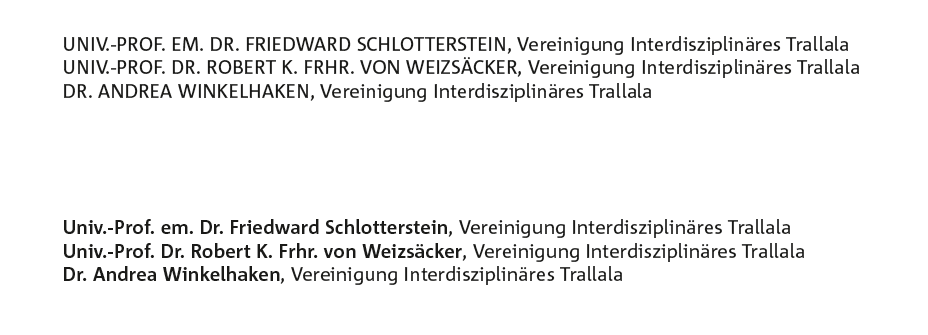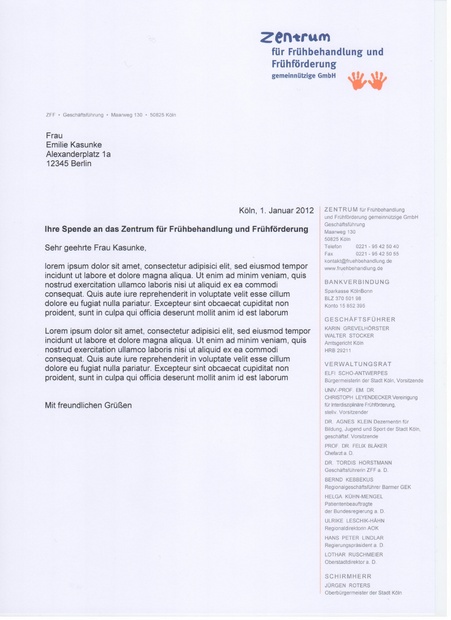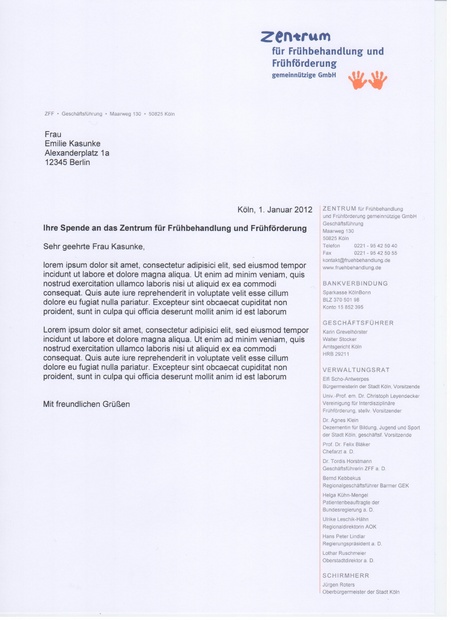
Abkürzung "em." - nur als Minuskel?
ob der häufigen Änderungen in der Besetzung unseres Verwaltungsrates drucken wir, eine gemeinnützige GmbH, die notwendigen Firmenangaben und die zu nennenden Namen direkt auf unser Geschäftspapier.
Namen und Titel der Honorationen sind hierbei jeweils in Majuskeln gesetzt, die Provenienzangabe dann in normaler Klein- und Großschreibung.
Nun haben wir einen emeritierten Professor dazubekommen, dessen Namen ich, dem oben beschriebenen Schema folgend, so gesetzt habe:
UNIV.-PROF. EM. DR. FRIEDWARD SCHLOTTERSTEIN, Vereinigung Interdisziplinäres Trallala
Nun beschwert der Mann sich wie folgt:
"Es ist [...] höchst ungewöhnlich bei meiner Angabe das "em." in Großbuchstaben zu schreiben. Sie sollten das ändern."
Und, soll ich das ändern? Ich habe nach längerer Recherche keinen Hinweis darauf gefunden, dass ich ausgerechnet die Abkürzung "em." nicht als Majuskel setzen darf, so dass ich die Frage gerne in dieses Forum geben möchte: Muss das kleine minuskelige "em." künftig alleine zwischen all den großen Buchstaben stehen?
UNIV.-PROF. em. DR. FRIEDWARD SCHLOTTERSTEIN, Vereinigung Interdisziplinäres Trallala
Sieht irgendwie komisch aus.
Aber wenn er recht hat, kriegt er das natürlich so ...
Es ist höchst ungewöhnlich den Titel und den Namen in Großbuchstaben zu schreiben. Ich würde das gemischt schreiben und – wenn überhaupt nötig – durch eine Fettung auszeichnen. Alles versal und nur das "em." dazwischen klein geht gar nicht.
Entweder den ganzen Titel groß oder gar nicht.
In wissenschaftlichen Werken wird übrigens oft nur der Nachname aus Kapitälchen gesetzt, Vorname und Titel aber gemischt (normal). Eine Möglichkeit wäre auch, Namen und Titel normal zu setzen und die Provenienzangabe kursiv.
Zeige doch mal ein Gestaltungsbeispiel, wie das Ganze da aussieht.
Alle Arten der Schreibung sind möglich, solange sie konsequent umgesetzt werden.
DR. MED.
PROF. EM. DR. PHIL.
Prof. em. Dr. iur.
prof. dr. h.c. dr. dent.
Das em. klein in eine Versalzeile zu setzen, wäre falsch. Der Professor irrt.
Fette Schriften für Namen sind nach alten Akzidenzregeln unzulässig, denn, so hieß es einst: "Man schreit den eigenen Namen nicht." Diese Regel gilt in meiner Werkstatt bis heute, und bislang sah jeder Kunde sie sofort ein.
Alle Arten der Schreibung sind möglich, solange sie konsequent umgesetzt werden. … Fette Schriften für Namen sind nach alten Akzidenzregeln unzulässig …
Das widerspricht sich aber. Zumal ein versal gesetzter Name wesentlich lauter daherkommt als ein gefetteter. Wir sprechen ja immer noch vom Briefbogen, da würde ich (wie oben schon gesagt) alles gemischt schreiben.
Eine fette Futura in Korpus ist sehr viel auffälliger als eine magere Garamond in Petit-Versalien, daran kann kein Zweifel bestehen. Es kommt auch auf die Größe an. Fette Schriften stechen immer hervor, deshalb werden sie auch in der Belletristik nicht zur Auszeichnung verwendet, sondern Versalien, Kapitälchen und Kursive. Fette Schriften sind überhaupt nur in der Reklame nötig oder in Boulevardzeitungen, sonst immer entbehrlich.
Wenn der Briefbogen schon eine Konstante hat, also Namen mit Titel in Majuskeln, dann kann man dabei bleiben. Es geht ja um eine pragmatische Lösung in einem vorhandenen Entwurf, nicht um eine neue Gestaltung. Namen in Versalien sind für Akzidenzen eine bevorzugte Lösung, seit langer Zeit, siehe diverse Briefbogen von Thomas Mann usw.
Thomas Mann ist jetzt nicht das aktuellste Beispiel. Die Tradition in allen Ehren, aber der Satz eines heutigen Briefbogens darf sich ruhig den heutigen Seh- und anderen Gewohnheiten anpassen.
Ich finde die Versalien wesentlich lauter …
M. E. wirken die fetten Namen eher plump und die Versal-Namen würdevoller. Es ist halt auch die Frage wie man schreit ...
Wenn möglich, würde ich ja Kapitälchen einsetzen, aber das war ja nicht die Frage.
… Wenn möglich, würde ich ja Kapitälchen einsetzen …
Wenn möglich, würde ich gar nicht auszeichnen ;-)
Ungesperrte zu große Versalien gegen halbfette Schrift sind natürlich auffälliger wegen ihrer Häßlichkeit. Ich meinte richtig gesetzte Versalzeilen, also etwas kleiner und vor allem ausgeglichen und spationiert.
Dass ich das in der Kürze der Zeit nicht feingefrinkelt habe, bitte ich nachzusehen.
Eine Versalzeile besteht für mich zunächst aus Großbuchstaben, die in ihrer Größe nicht verändert sind. Du sagst, dass du sie etwas kleiner setzen würdest – nach welchen Kriterien richtet sich die Größe? (Vielleicht sollte man das auslagern, ich weiß nur nicht wie …)
Mmh, die Schrift kleiner - wird schwierig, glaube ich. Zurzeit sind´s 7 Pt.
Aber ich merke schon - das wird ´ne schöne Aufgabe fürs neue Jahr!